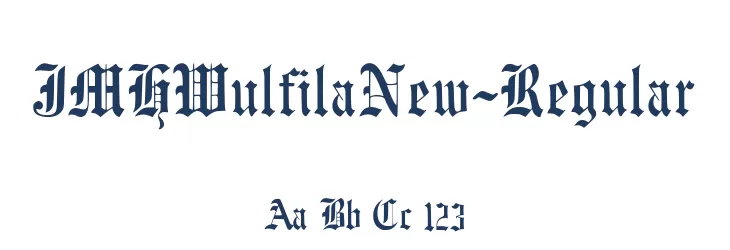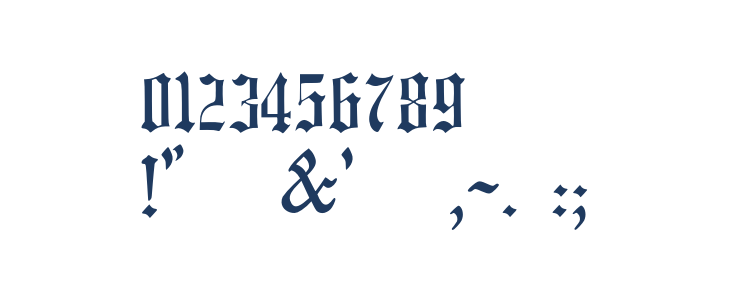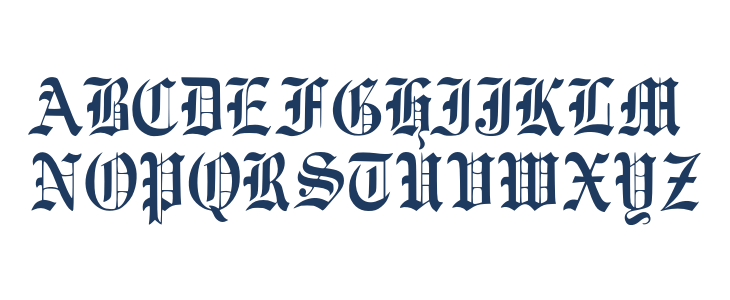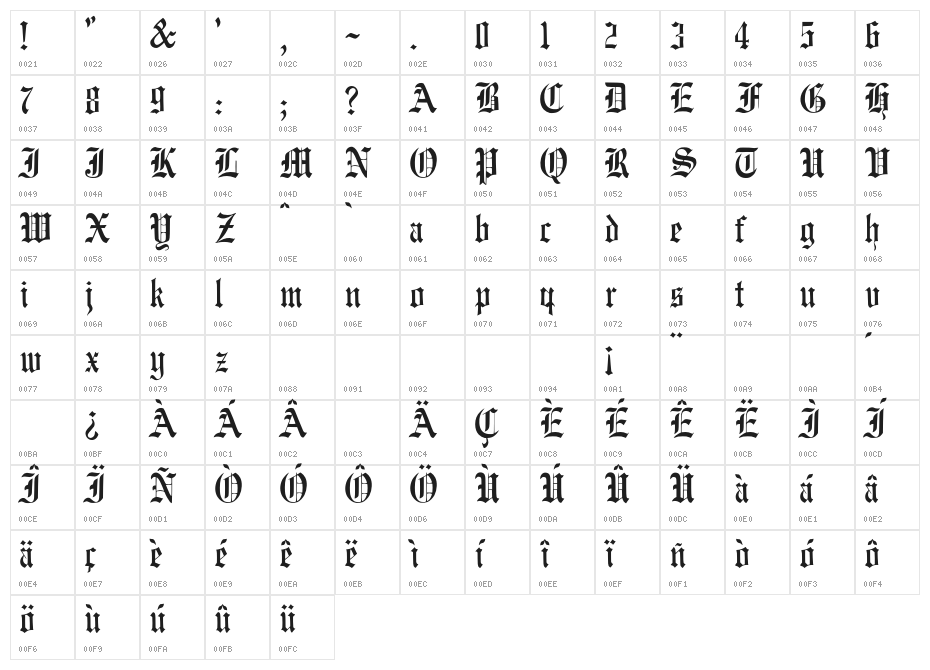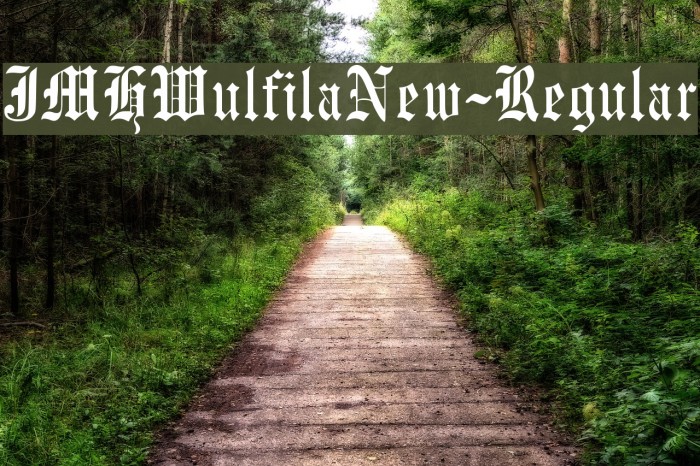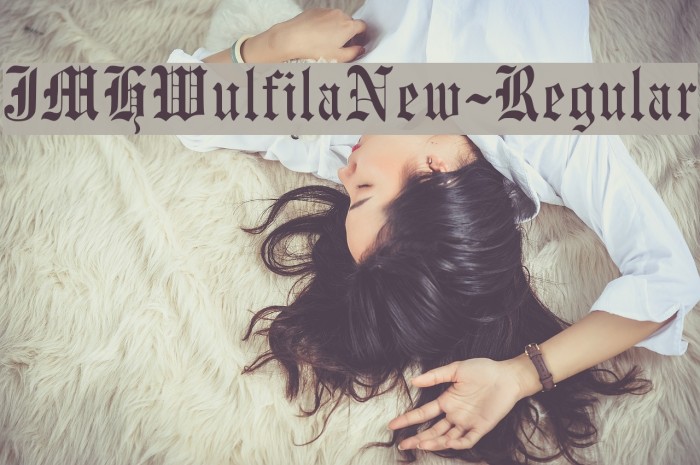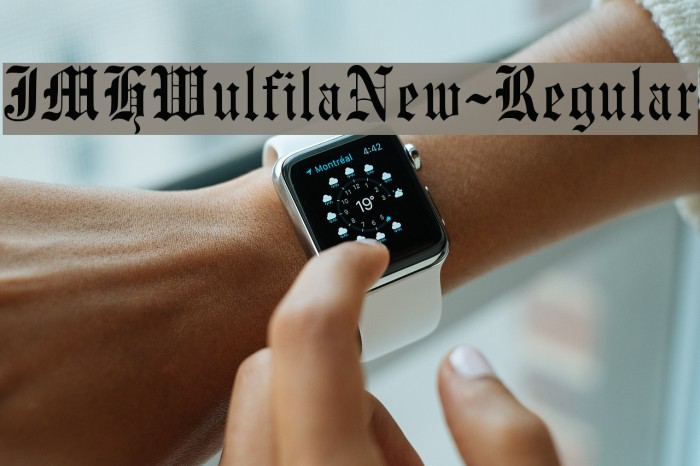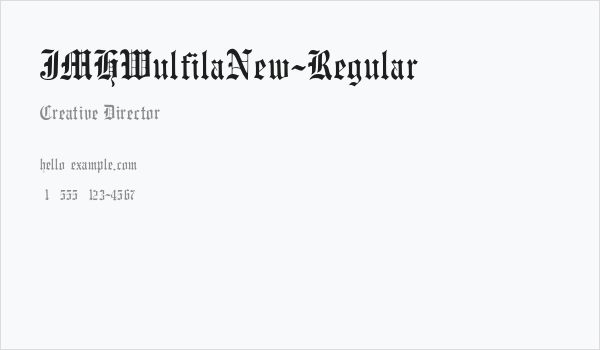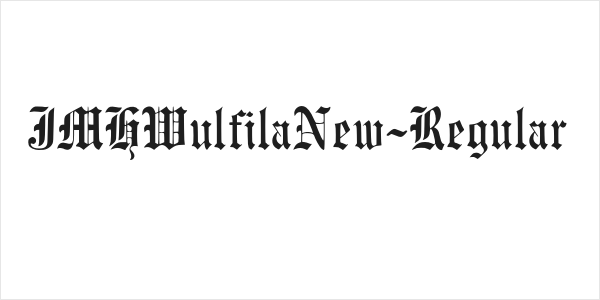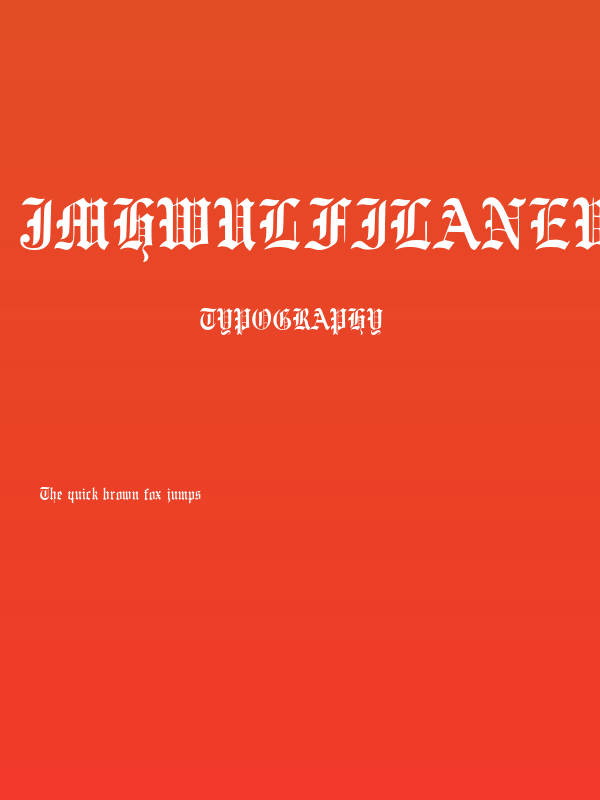
JMHWulfilaNew-Regular Font
| Estilo general | Gothic, Medieval |
| Caso de uso | Headlines, Logos, Decorative text |
| Proyectos propuestos | Ideal for projects that require a historical or gothic touch, such as book covers, posters, or branding for themed events. |